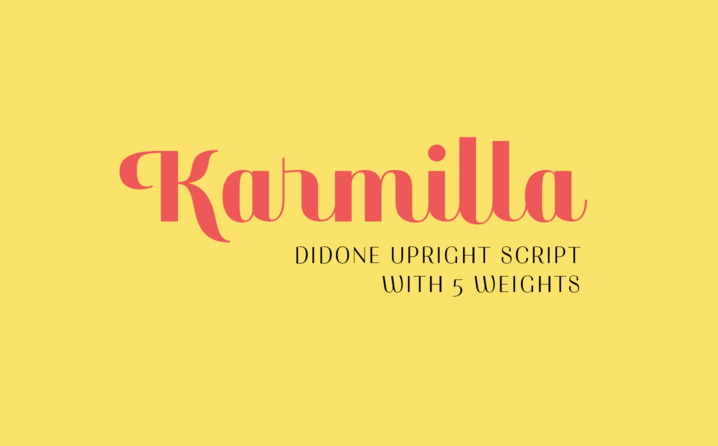
Introduzimos a Karmilla Font Family! Esta familia de fontes foi desenvolvida pelo designer Akufadhl. A Karmilla é uma tipografia de script, estilo Didone e upright. Possui um contraste robusto entre linhas grossas e finas. Apresenta uma característica feminina luxuosa e criando designs mais elegantes e clássicos. Com suporte para múltiplas linguagens baseadas em latim e uma ampla variedade de recursos, como Swash, Conjuntos Estilísticos e Caps Pequenos, a Karmilla se destaca por sua estética playfull e feminina. Este design original do designer Hamilton é ideal para projetos criativos que buscam uma linguagem elegante e moderna.